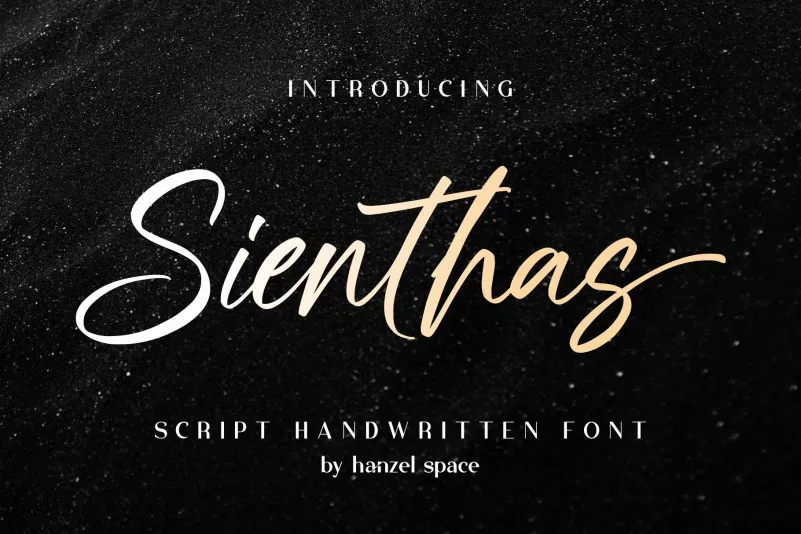
A Sienthas Font é uma elegante tipografia script moderna, criada pela Hanzel Studio, que traz ao design a delicadeza feminina do mundo das letras. Perfeita para aplicar em campanhas de marca, convites para casamentos e como frase de chamar atenção nos cartões personalizados. Também se destaca como uma escolha versátil para etiquetas e logotipos. Esta fonte é um ótimo recurso para quem busca unir sofisticação com a essência delicada do script em seus projetos visuais, seja em design de gráficos ou criações digitais. Sienthas pode tornar suas ideias ainda mais inovadoras e memoráveis.